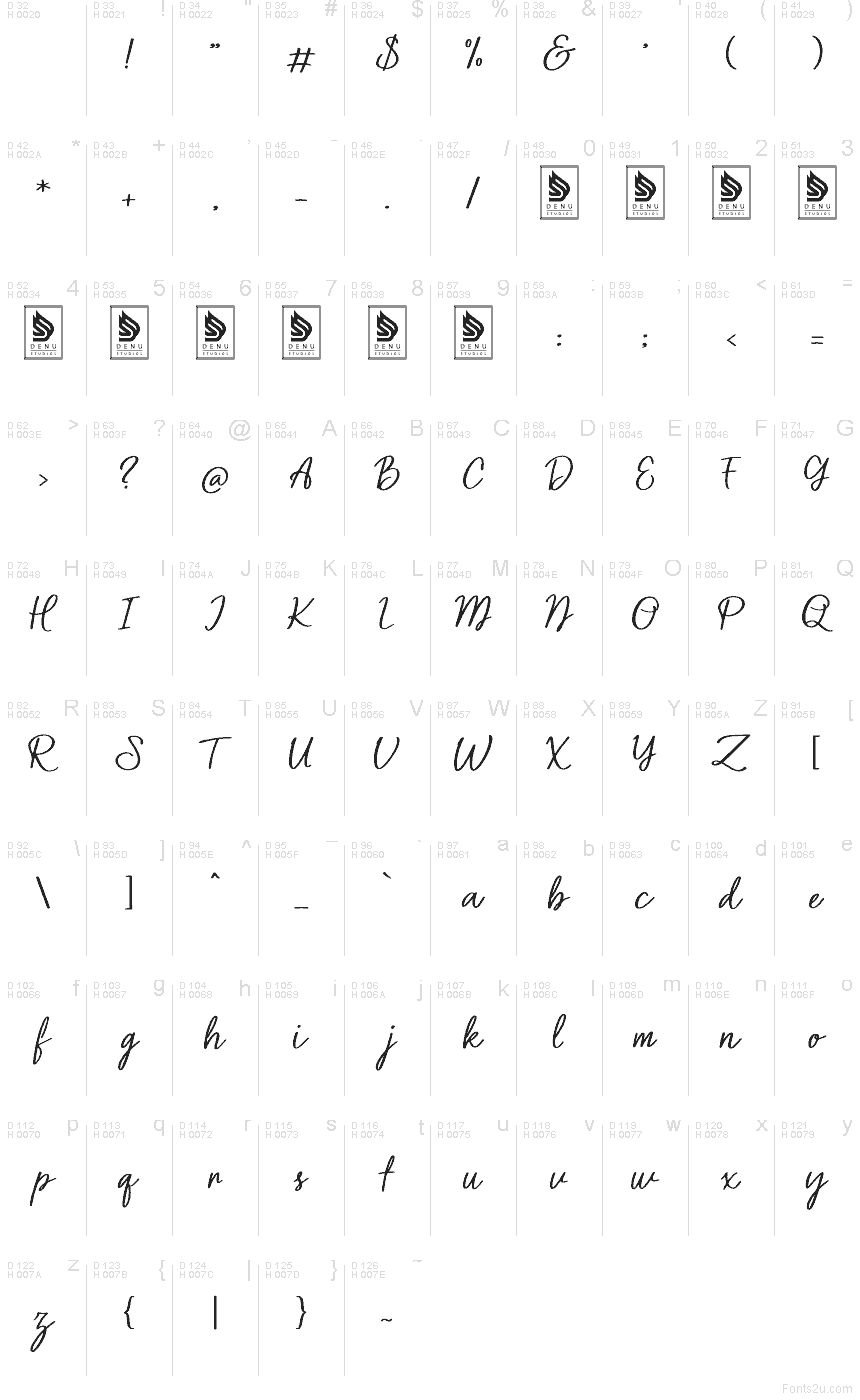
Babe Riesthy de Denustudios es una tipografía manuscrita gratuita con un aire fresco y a la moda. Sus letras se basan en trazos largos y curvos con uniones ligeras, mezclando un ritmo casual con algunos remates elegantes y fluidos que hacen que se sienta liviana en lugar de formal.
Es perfecta para branding, packaging de boutique, posts en redes sociales, portadas de revistas y papelería de bodas donde una fuente gratuita pueda ofrecer un toque personal sin complicaciones. Úsala en titulares cortos, bocetos de logotipos, tarjetas de título o tratamientos de nombres tipo monograma cuando quieras que los trazos iniciales y finales definan el estilo.